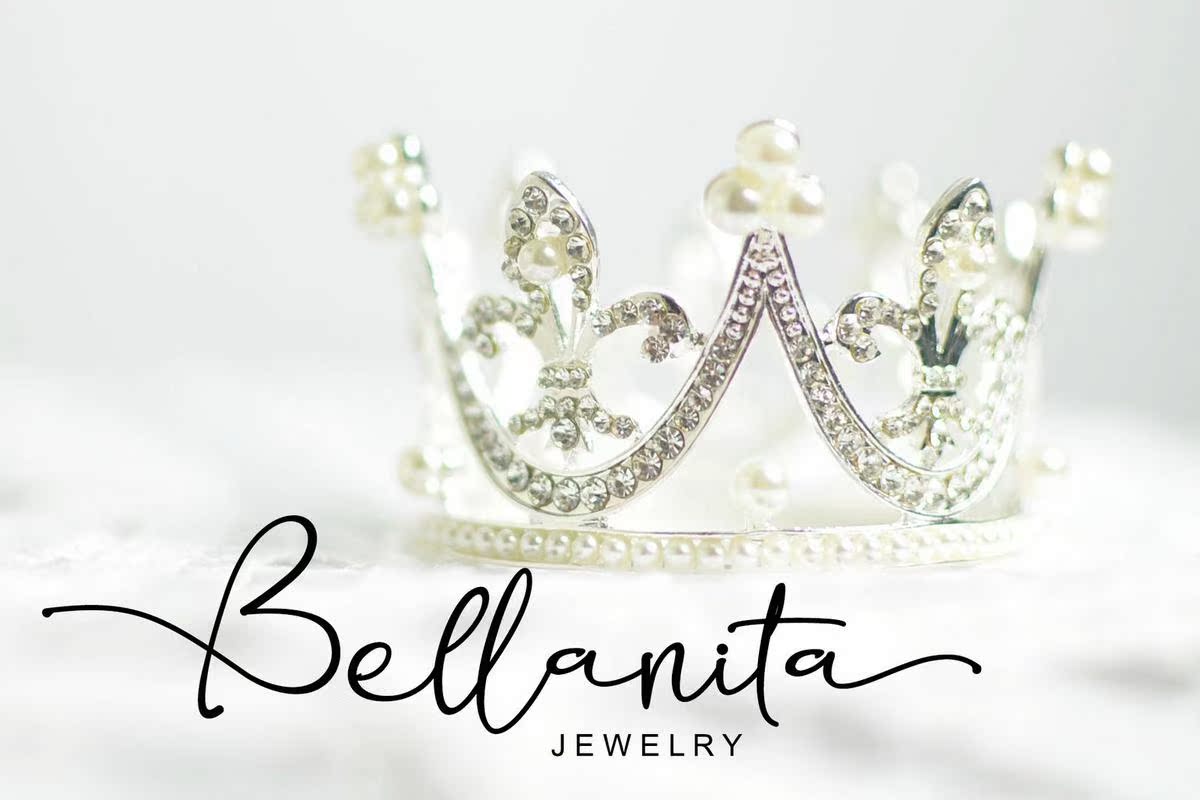
WolfriendFontIsAssignature并由文字工作室编写。它具有流动的文字,将为您的设计和WeetLook提供信息。Wolfriendfontisperfect;徽标、问候卡、包装设计、耐磨损性、工艺设计、任何项目、书名、婚礼宣传、包装等。WolfriendFontIsassignature并由文字工作室书写。它是流动的文字,将为您的设计提供信息和周末书籍。Wolfriendfontisperfect;徽标、问候卡、包装设计、耐磨性、工艺设计、任何项目、书名、婚礼宣传、包装等。